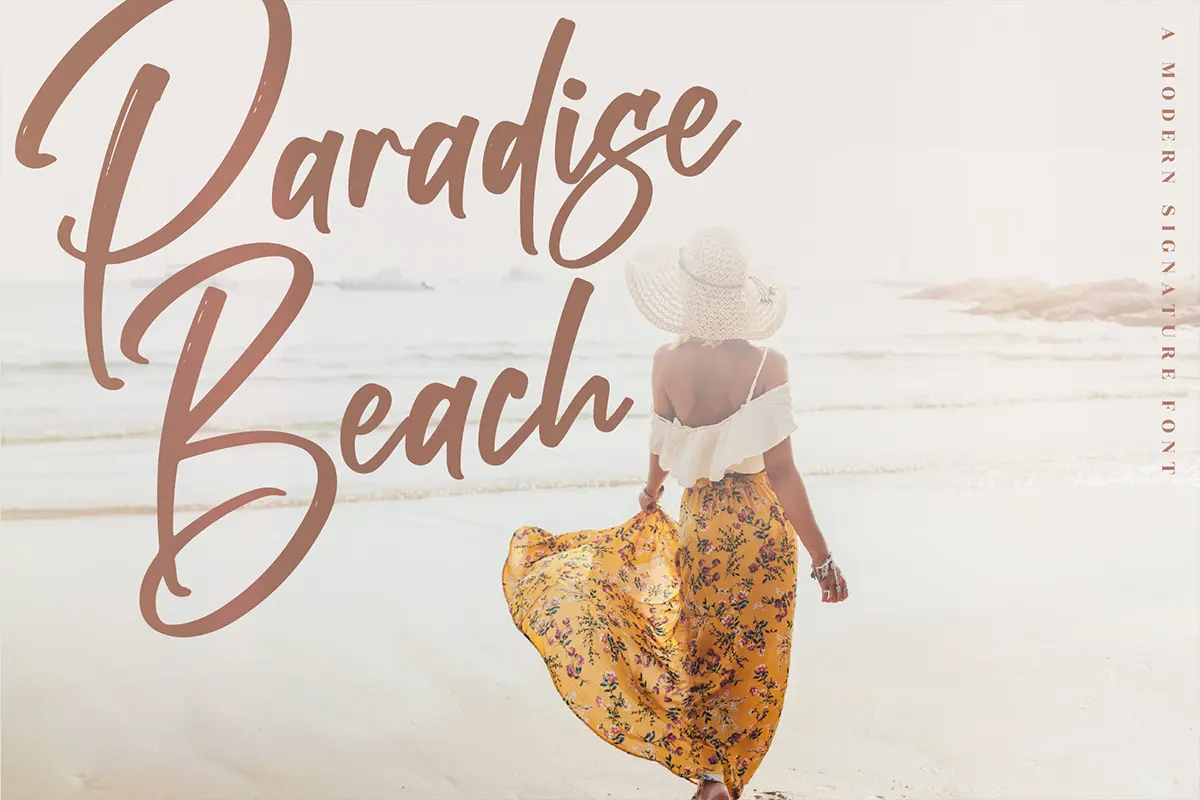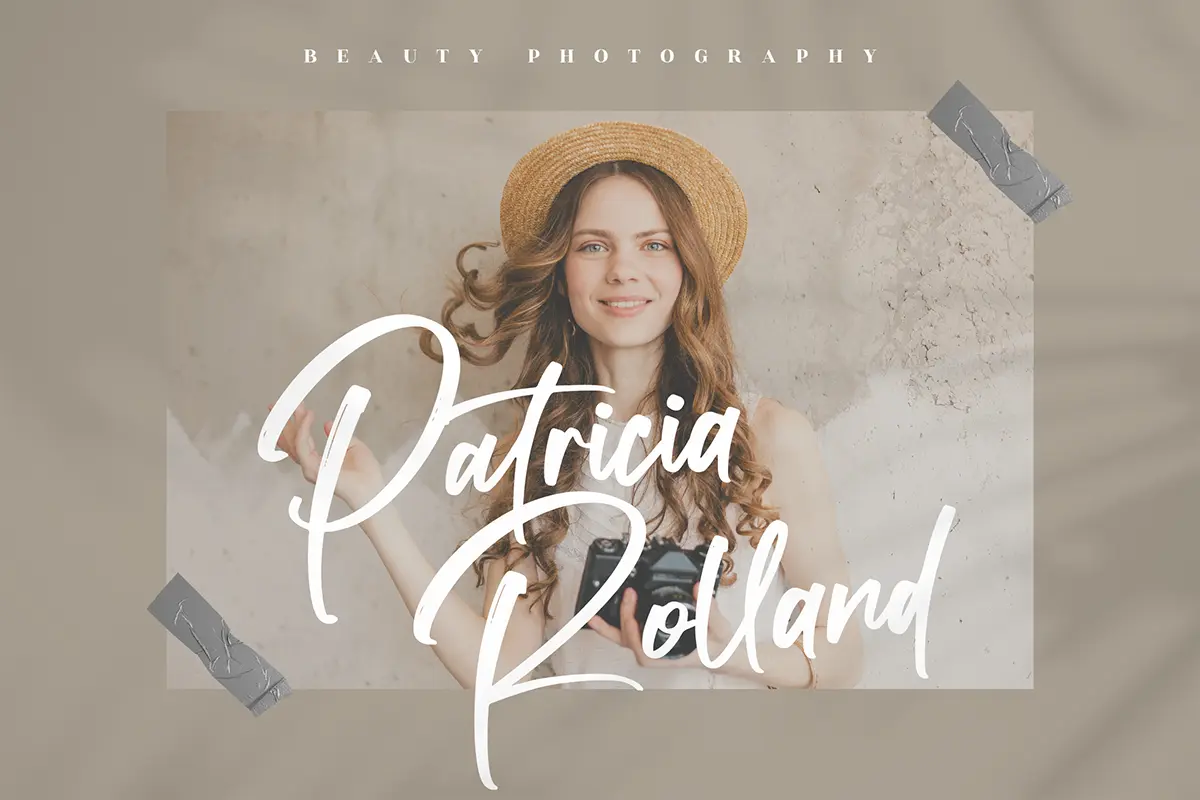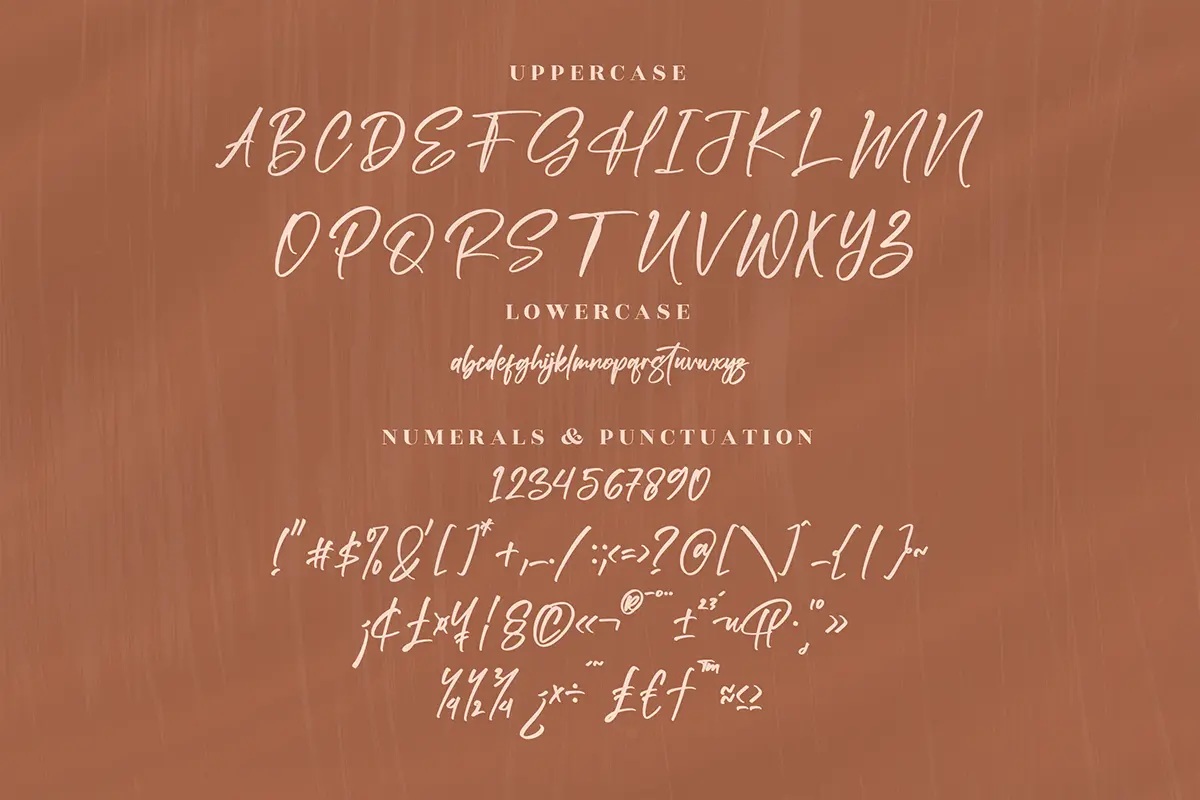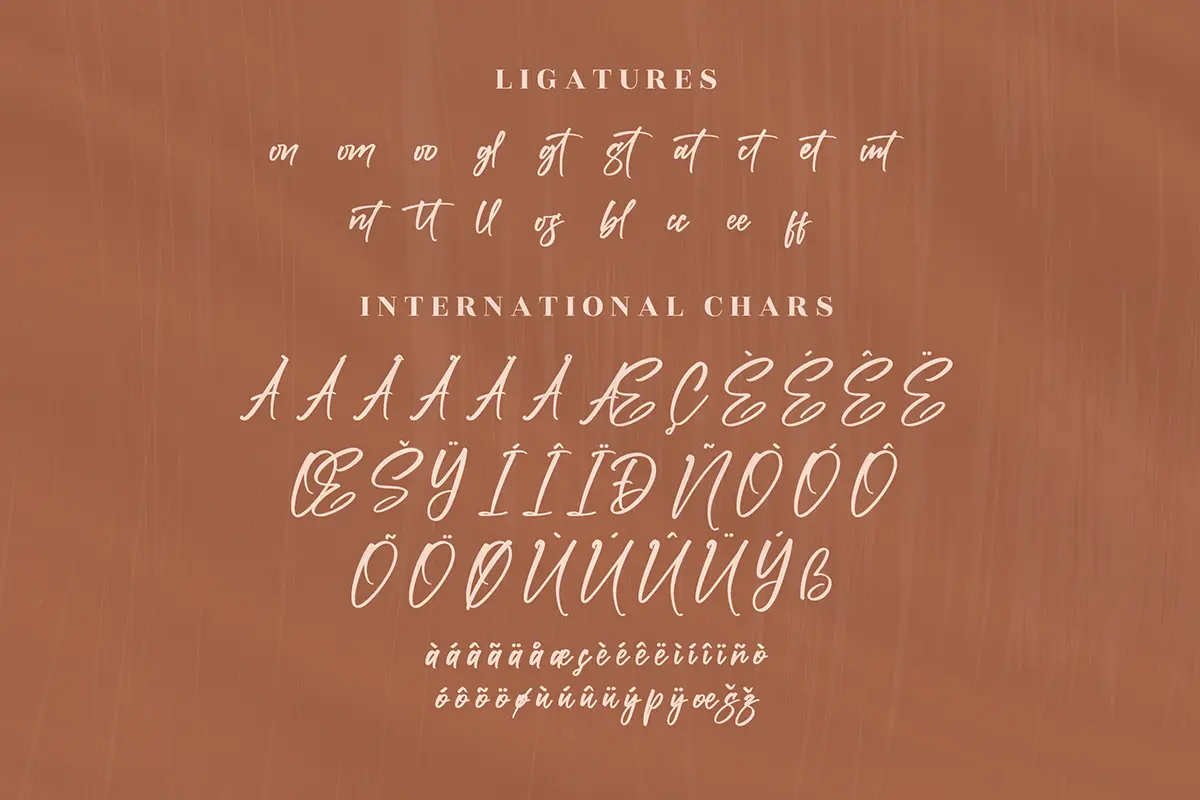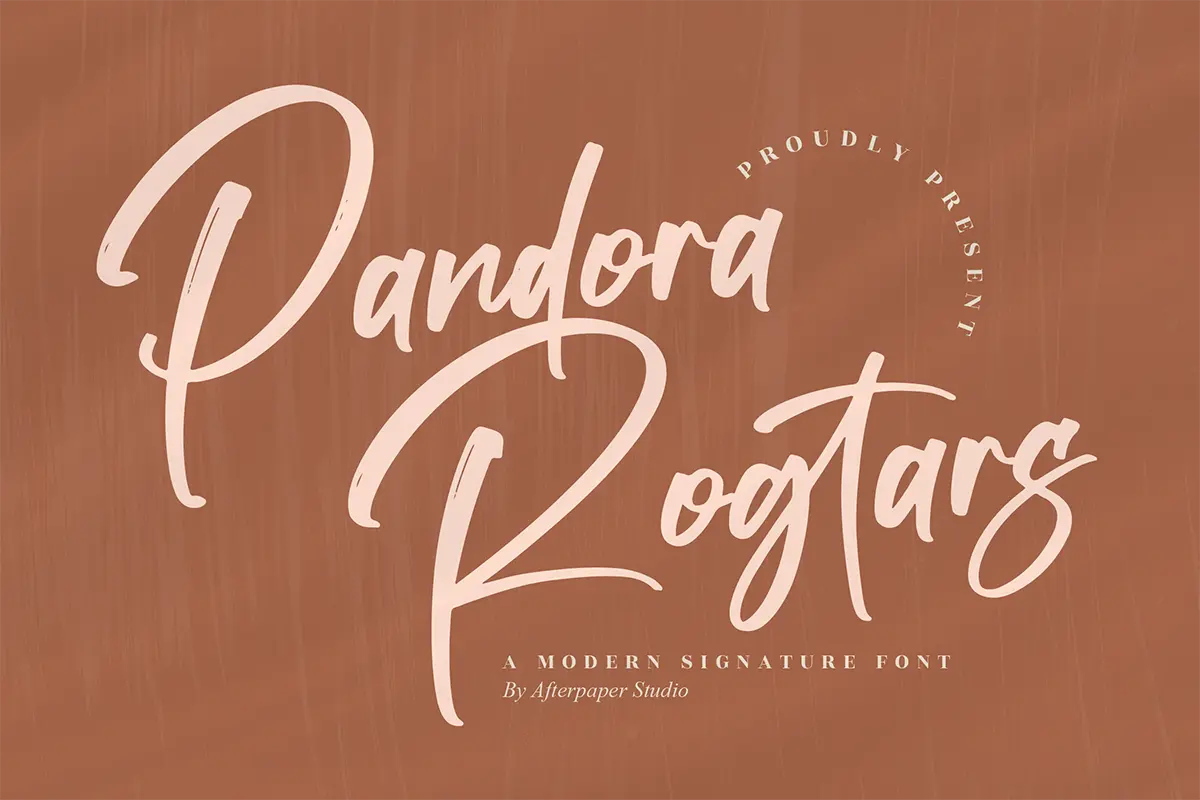
فونت انگلیسی شیک و زیبای Pandora Rogtars
فونت Pandora Rogtars یک فونت اسکریپت زیبا و شیک است که برای پروژههای متنوع طراحی شده. این فونت به طرحهای شما حس ظرافت و استایل خاص میبخشد و برای لوگوها، برندینگ، کارت دعوت، کارت تبریک، لیبل، عکاسی، واترمارک، رویدادهای خاص و بسیاری پروژههای دیگر مناسب است.
این فونت PUA Encoded است، به این معنا که میتوانید بهراحتی به تمامی گلیفها و سوئشهای تزئینی آن دسترسی داشته باشید و طراحیهای خود را حرفهایتر کنید.
⭐ ویژگیهای محصول:
- سبک اسکریپت زیبا و ظریف
- مناسب برای لوگو، برندینگ و کارتهای دعوت
- کاربردی در عکاسی و واترمارک
- ایدهآل برای رویدادهای خاص و طراحیهای هنری
- PUA Encoded برای دسترسی آسان به گلیفها و سوئشها
🎯 موارد استفاده:
- طراحی لوگوهای خاص و متمایز
- ساخت کارت دعوت و کارت تبریک شیک
- لیبل و بستهبندی محصولات
- واترمارک برای عکاسان و هنرمندان
- پروژههای برندینگ و هویت بصری